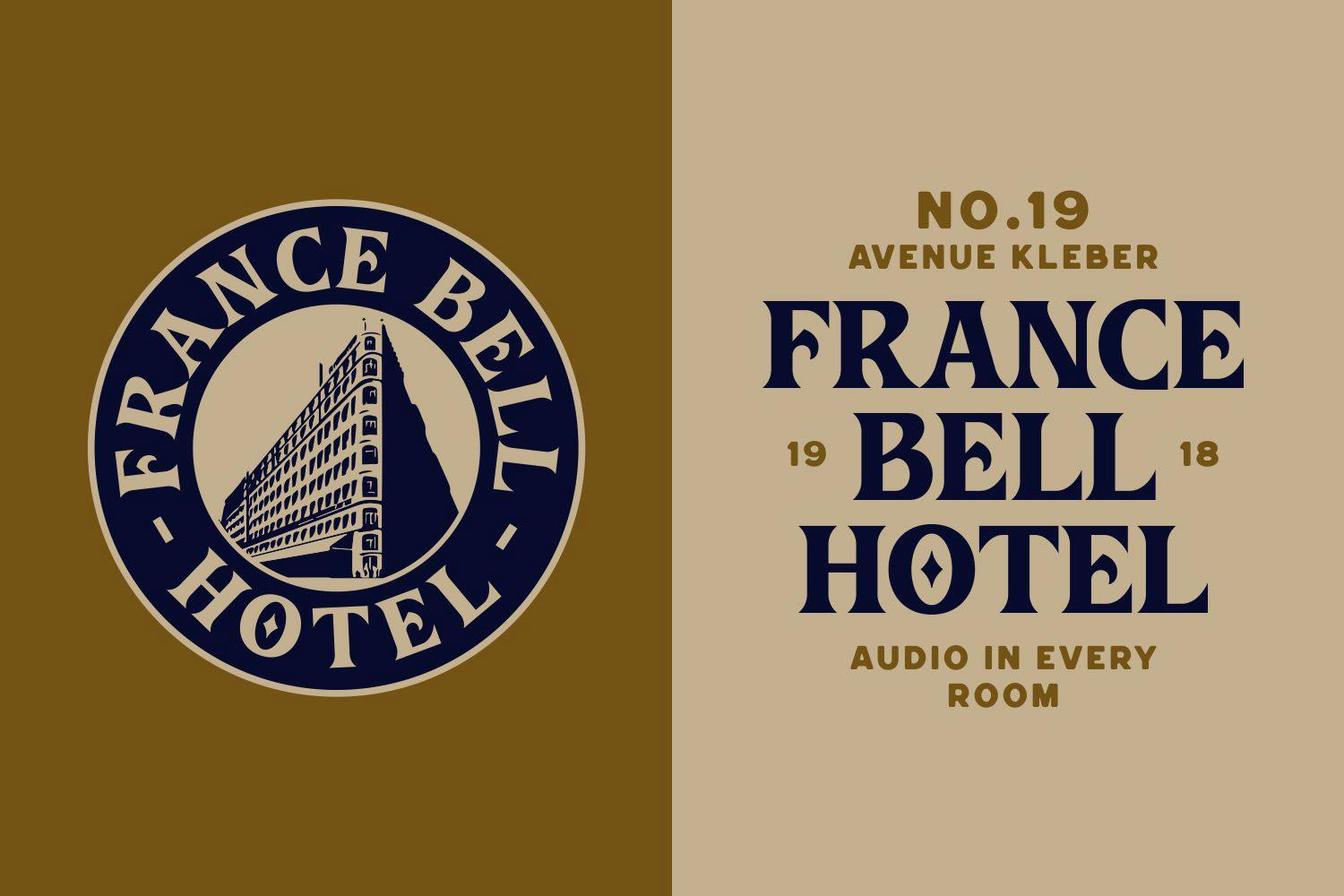
دانلود فونت نیک بوریش با طراحی وینتج جذاب
Nick Borish Vintage Font
فونت نیک بوریش، انتخابی عالی برای طراحی‌های وینتج و مدرن.
فونت نیک بوریش یک فونت وینتج است که از هنر و خطاطی زیبا الهام گرفته شده است. این فونت با شخصیت‌های طراحی منحصر به فرد خود، جلوه‌ای شیک و هنری به طراحی‌های شما می‌بخشد. نیک بوریش برای طراحی لوگو، بسته‌بندی، عبارات کوتاه یا عناوین بسیار مناسب است.
• طراحی وینتج و منحصر به فرد
• مناسب برای طراحی لوگو و بسته‌بندی
• قابل استفاده در پروژه‌های هنری و تبلیغاتی
• ایجاد جلوه‌ای شیک و جذاب در طراحی‌ها